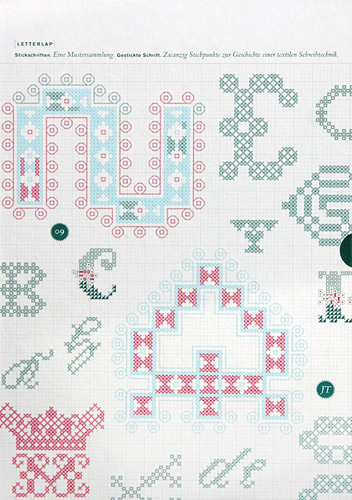
Literatur zur Typografie
[h=2]Anfänger/Grundlagen[/h]
Max Bollwage
Typografie kompakt
Das Buch vermittelt typografisches Basiswissen auf knappe und anschauliche Weise. Es ist praxisgerecht aufgebaut aus Antworten auf Fragen, die der Computer stellt nach Format, Satzspiegel, Schrift, Schriftgröße und Entfernung, Abstände, Gliederung u.v.a.m.
Ein Kapitel befasst sich ausführlich mit der Rolle der Typografie im Corporate Design.
Das Buch bietet ein neues Ordnungssystem nach Form und Struktur, das den Überblick über die Schriften erleichtert und hilft, eine passende Schrift zu finden.
Jaroslav Andel
Avant-Garde Page Design 1900–1950
Jaroslav Andel beleuchtet in seinem Buch die Entwicklung der Avantgarde-Typografie zu Beginn des 20. Jahrhunderts. Über diverse Vorläufer und Pioniere des typografischen Experiments im 18. und 19. Jahrhundert, spannt er einen Bogen zu den typografischen Arbeiten der Kubisten, Expressionisten, Futuristen, Dadaisten, Konstruktivisten, De Stijl, Vertretern der Neuen Typografie, u.a. Parallel werden die wechselseitigen Einflüsse und Beziehungen zwischen der experimentellen Typografie und der bildenden Kunst, Architektur, Film und Fotografie beleuchtet. Entgegen des Titels endet Andel bereits Mitte der 1930er mit seinen Ausführungen; einen Ausblick auf folgende (experimentelle) Typografie-Generationen gibt er nicht.
Das Buch ist dreisprachig (deutsch, englisch, französisch) gesetzt und beinhaltet mehr als 460 – meist farbige – Abbildungen in guter Qualität.
Max Bollwage
Buchstabengeschichte(n)
Wie das Alphabet entstand und warum unsere Buchstaben so aussehen.
Mit Bildern hat es angefangen – Aus der Wüste durch Kanaan übers Meer – Wir schreiben noch immer römische Buchstaben – Dem Schreiben in Wachs verdanken wir die Kleinbuchstaben – Die Schriften mit dem Knick – Die Antiqua, seit 600 Jahren immer wieder neu entworfen – Die Schönen und die Schnellen geschrieben und gedruckt – Warum manche Schriften dicke Füße haben, andere dagegen gar keine – Die Schrift geht mit jedem, oder die Macht des Zeitgeistes – Druckschrift heute
Alfred Alisch
Richtlinien für den Satz fremder Sprachen
Das Buch ist eine Neufassung des 1929 erschienenen gleichnamigen Werks von Paul Grunow. Knapp faßt es die satztechnischen Besonderheiten von 37 Sprachen zusammen, geordnet nach Alphabet bzw. spezifischen Akzentbuchstaben, Aussprache, Abkürzungen, Interpunktion, Daten, Fußnoten, Maß- und anderen Einheiten, Zeitangaben, Silbentrennung, Auszeichnungsgebräuchen und dergleichen.
Es existiert keine aktuelle Auflage, antiquarische Exemplare sind rar. Obwohl einzelne Angaben, wie zum Beispiel über Währungen, inzwischen veraltet sind, bleibt in der Summe ein recht brauchbares Arbeitsmittel für den Schriftsetzer, der gelegentlich mit Fremdsprachensatz befaßt ist und sich einen allgemein gehaltenen Überblick über die jeweiligen Satzregeln verschaffen muß.
Samuel Marty, Richard Frick
Der Schriftenfächer — Eine Entdeckungsreise
Der neue Schriftfächer zeigt auf einer Blattseite charakteristische Buchstaben der betreffenden Schrift. Die Besonderheiten werden hervorgehoben und benannt. Anhand dieser Buchstabenfolge werden gleichzeitig die horizontalen Größenverhältnisse der Schrift vermessen. Weiterhin werden die Hauptbuchstaben (A bis Z und a bis z), die Ziffern und einige Satzzeichen abgebildet. Letzlich werden folgende Informationen gelistet: Schriftentwerfer; Jahr des Erscheinens der Schrift; Schriftname im Schriftmenü; Anzahl der Schnitte, die der Zürcher Hochschule der Künste und der Zürcher Fachhochschule zur Vergügung stehen (!); Klassifizierung nach DIN 16 518; Herkunftsnachweis.
Auf der Rückseite wird das Wort »Typografie« in 24 Punkt wiedergegeben. Danach folgt ein Text, der den Nutzer die Schrift in Lesegröße beurteilen lässt. Diese Texte sind gleichzeitig ein Glossar typografischer Begriffe, wie zum Beispiel Schattenachse, Duktus oder Unterlänge. Die Schnitte, die den beiden Schulen vorliegen, sind hier ebenfalls abgebildet.
Im Vorfeld werden Literaturhinweise genannt und Internetverweise gegeben. Auf fast zwanzig Blatt wird über Terminologie der Schrift, Schriftlinien/-höhen, Schriftproportionen, Strichstärken, Schriftbreiten, Schriftlagen, Monospace-Schriften, Schriftschnitt/-familie, Schriftsippe/Hybridschriften, Schriftmischung, Geviert, geviertbasierende Leerräume, geviertbasierende Strichlängen, OpenType-Schriftformat und die DIN-Klassifikation 16 518 informiert.